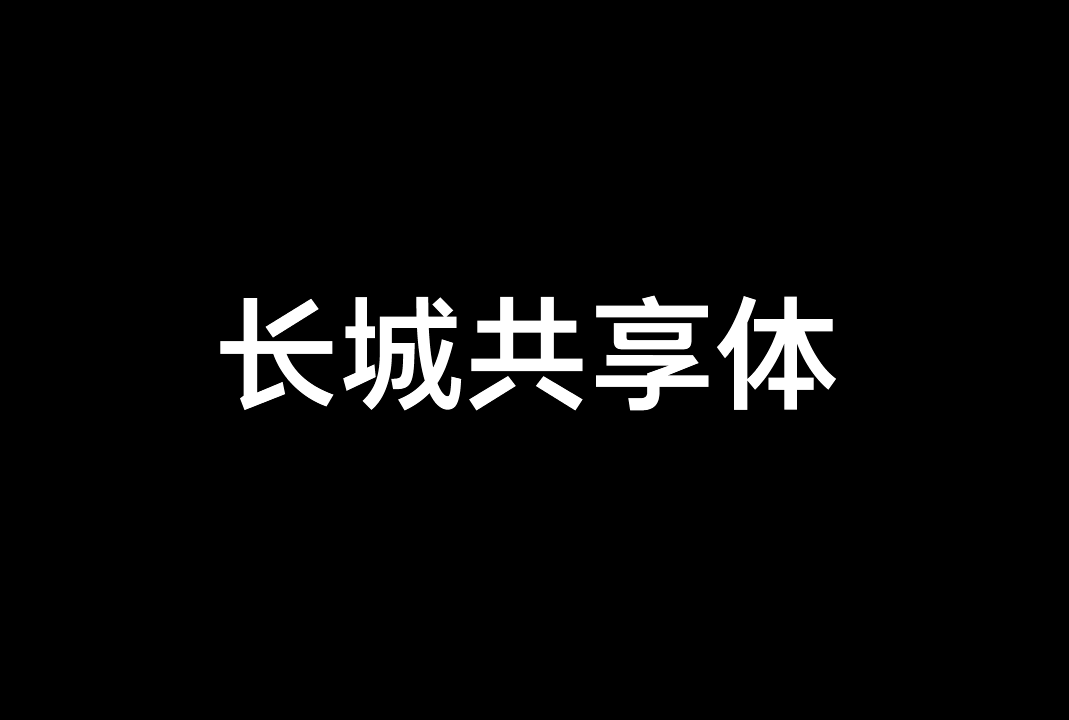
长城共享体(GWM Sans)是由长城汽车发布的一款多语言免费字体,于官网声明开放商用。
长城共享体(GWM Sans)是长城汽车携手蒙纳字库专为车载系统设计的一款字体,字体秉承“安全、高效、自然”的设计理念,巧妙兼容圆润不失力量感的设计,车载阅读无压力。其设计不仅使整体界面更加时尚、年轻化,还大幅提升了易读性和辨识度,从而显著增强了车载界面的安全性和舒适感。
GWM Sans Latin(拉丁语)
该字体文件包含英语、法语、德语、印尼语、西班牙语(拉丁美洲、欧洲)、俄语、葡萄牙语(巴西)、越南语、乌克兰语、丹麦语、荷兰语、挪威语、瑞典语、意大利语、葡萄牙语(葡萄牙)、土耳其语,拓展至W1G水平,支持超170+语言,有 961 个字符, 3 种字重。
GWM Sans Chinese(中文)
该字体文件包含中文简体、中文繁体,生僻字,标点符号,符合GB18030-2022 L2级别,有 28775 个字符,3 种字重。
GWM Sans Hebrew(希伯来语)
该字体文件有 50 个字符,3 种字重。
GWM Sans Arabic(阿拉伯语)
该字体文件包含阿拉伯语、乌兹别克语、吉尔吉斯斯坦语、哈萨克斯坦语,有 120 个字符, 3 种字重。
GWM Sans Thai(泰语)
该字体文件有 256个字符,3种字重。